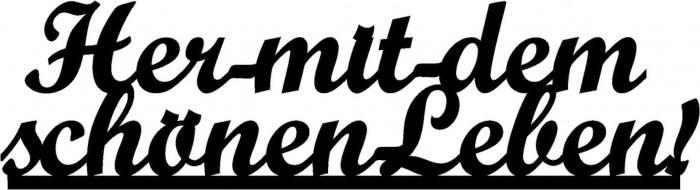
Schriftart zum auslasern von Wörtern in MDF gesucht
ich suche Schriftarten, mit denen ich Wörter als Objekte aus MDF lasern kann.
Dabei sollen die i-ä-ü-ö-Punkte möglichst verbunden sein, also "drankleben", damit sie nicht abfallen.
Gern kann es auch eine insgesamt verbunden Schrift sein (Schreibschrift), und ganz phantastisch wäre es noch, wenn die Buchstaben wie f, g und j nicht dreistöckig wären, bzw. nicht nach unten gehen, damit das Wort stehen kann.
Natürlich kann ich das in Illustrator entsprechend erstellen, aber es wäre sehr viel einfacher, wenn es schon eine fertige Schriftart gibt.
Hat jemand eine Idee? Ich bin auch schon dankbar für Fachbegriffe, mit denen ich selbst nach einer solchen Schriftart suchen kann - wenn es sowas überhaupt gibt...
Ich habe mal ein Beispiel angehängt, wie es aussehen könnte.
Das sind auf jeden Fall schon mal gute weitere Spuren, ich sehe schon, die Pünktchenproblematik haben noch mehr... Wahrscheinlich wird es notwendig, eine Schrift entsprechend umzugestalten, damit sie laserfähig wird.